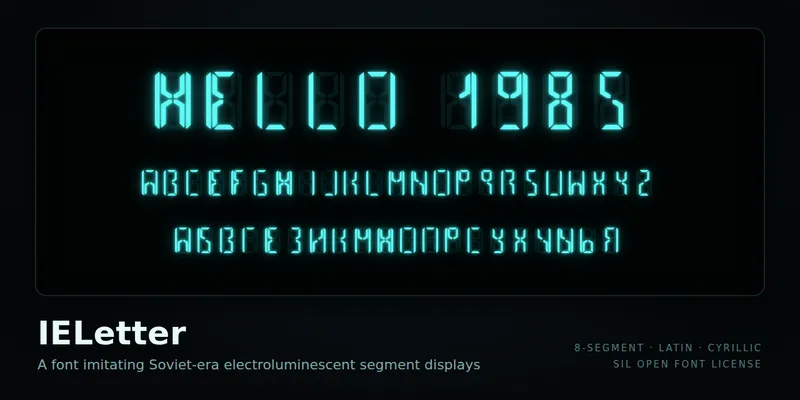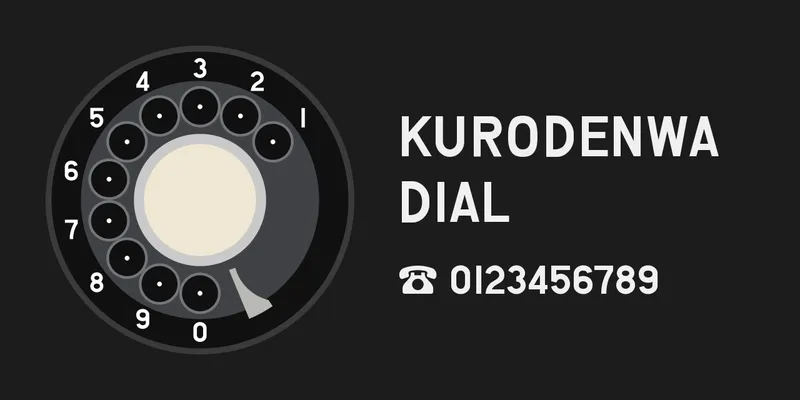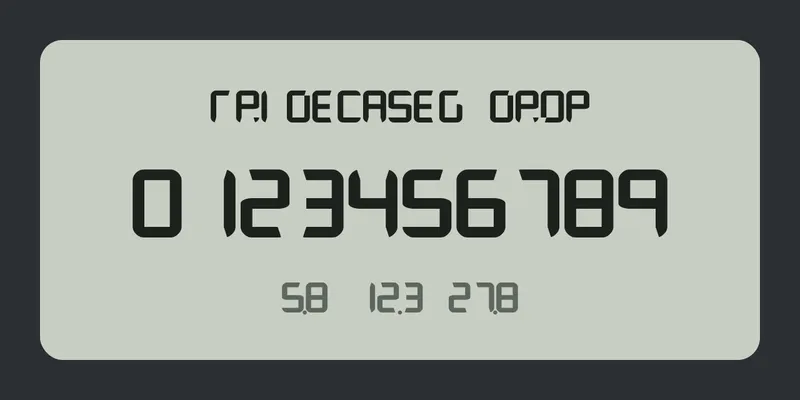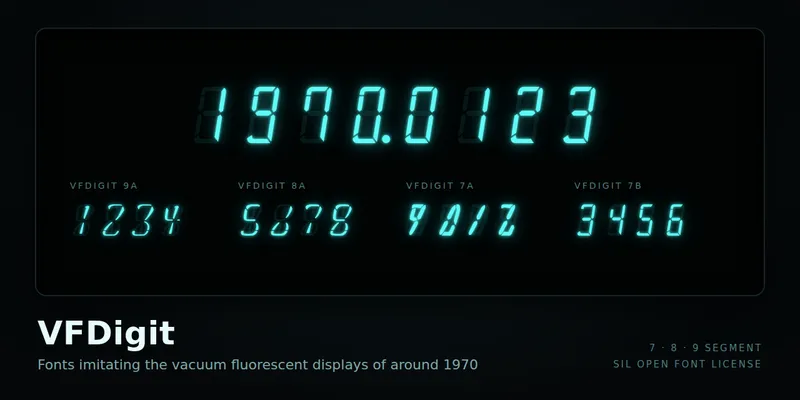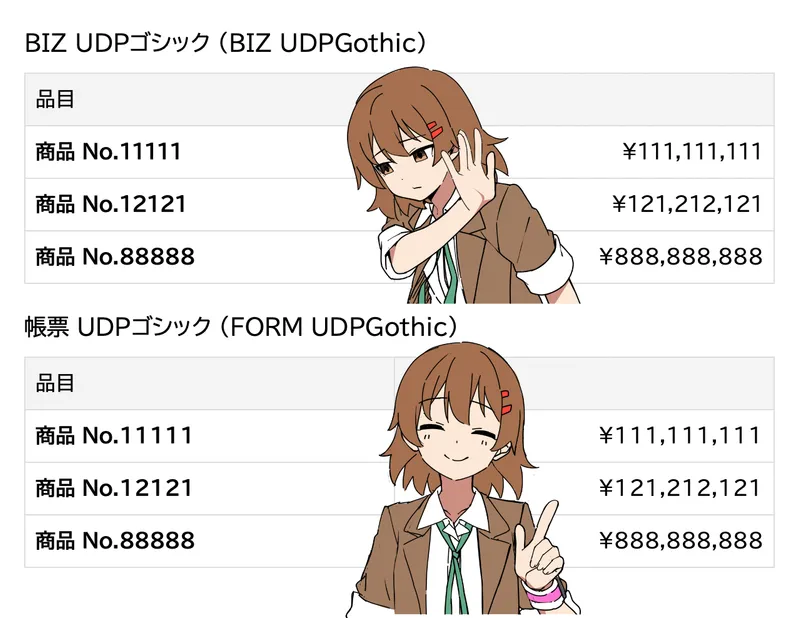
液晶風の背景に、Tridecaseg Drop で「TRIDECASEG DROP」「0123456789」「5.8 12.3 27.8」と表示した見本
血糖測定器の液晶の13セグメント文字フォント Tridecaseg Drop
血糖・ケトン測定器「FreeStyle Optium Neo」(アボット社)の液晶に表示される、特徴的な13セグメントの文字をもとに作ったフォント「Tridecaseg Drop」です。13本のセグメントで、英字の大文字と小文字も表現しています。無料(SIL Open Font License)です...
黒電話のダイヤルの絵と、黒電話ダイヤルで書いた「KURODENWA DIAL」「☎ 0123456789」
黒電話のダイヤルの数字フォント 黒電話ダイヤル
黒電話(600形)のダイヤル盤に書かれた数字と、指穴の中の点を写真から再現したフォント「黒電話ダイヤル」です。英字と記号、丸数字、☎ も収録しています。無料(SIL Open Font License)で公開しています。
IELetter の見本。黒地に青緑色で「HELLO 1985」と、ラテン文字とキリル文字が並ぶ
ソ連時代の EL ディスプレイ風フォント IELetter
1980年代のソ連で軍用に作られたとされる EL ディスプレイ「IEL-0-VI」を模した、等幅のフォント「IELetter」です。無料(SIL Open Font License)で公開しています。
VFDigit の見本。黒地に青緑色で「1970.0123」と、VFDigit 9A・8A・7A・7B の数字が並ぶ
VFD 風デジタル数字フォント VFDigit
1970年前後の電卓に使われていた蛍光表示管(VFD: Vacuum Fluorescent Display)の数字の書体を模した、等幅のデジタル数字フォント「VFDigit」です。9A・8A・7A・7B の4書体を、無料(SIL Open Font License)で公開しています。
帳票 UDPゴシック
モリサワ「BIZ UDPゴシック」の「1」と「1(全角)」の幅のみを変更し、数字(0〜9)を等幅にしたフォント「帳票 UDPゴシック (FORM UDPGothic)」です。 「BIZ UDPゴシック」を使いたい! でも、数字は等幅にしたい。でも、等幅の「BIZ UDゴシック」の数字は細すぎる! と...
帳票 UDP明朝
モリサワ「BIZ UDP明朝」の「1」と「1(全角)」の幅のみを変更し、数字(0〜9)を等幅にしたフォント「帳票 UDP明朝 (FORM UDPMincho)」です。 「帳票 UDPゴシック」を作ったので、明朝も作りました。